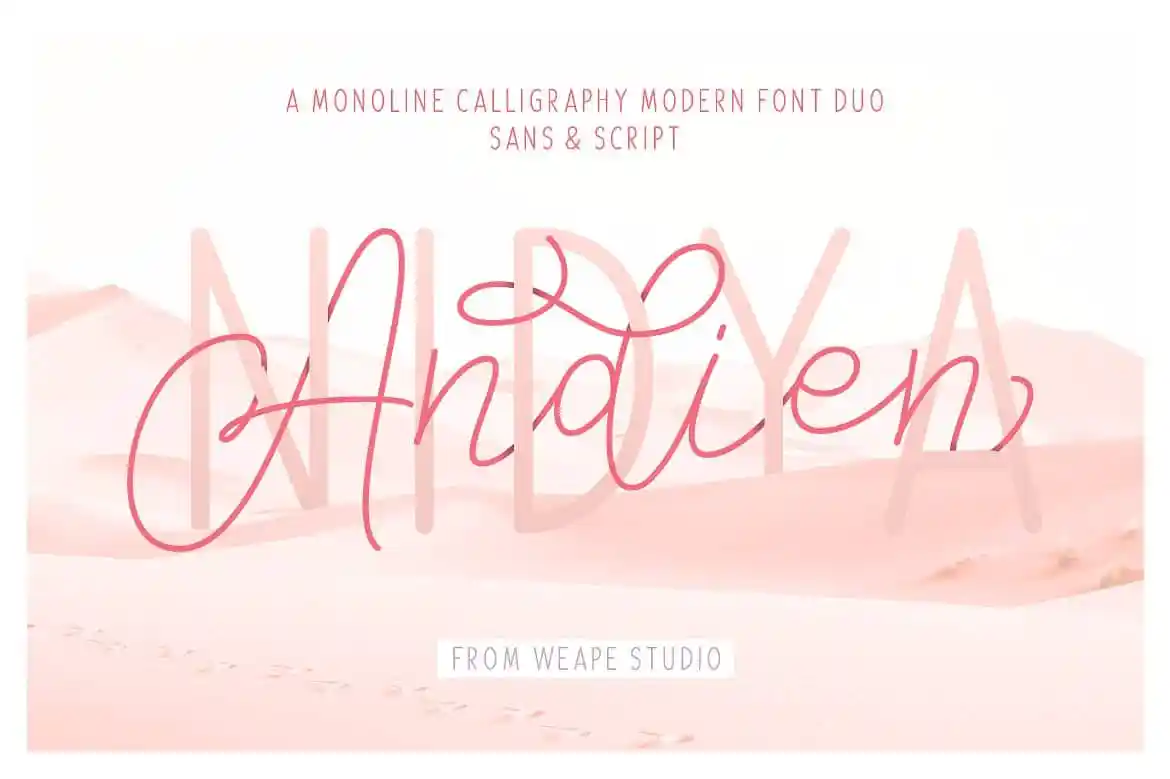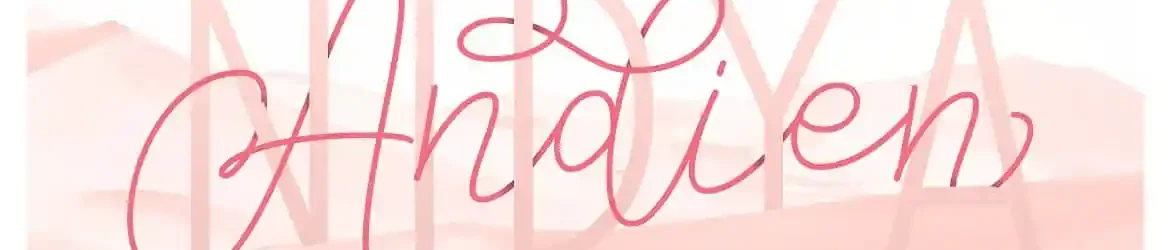
Olá! Estou aqui uma combinação moderna de serif e script, criada pelo 0001themes, no estilo de fontes de registro. Este é um duo de fontes que inclui a sofisticada Andien Nidya Script, uma fonte monoline com traços semicurvos e o sans-serif contemporâneo. A fonte moderna Andien Nidya traz à tona uma modernidade única, combinando características de calligrafia monoline com estilo de script, criando um duo perfeito para designers que buscam um toque único e sofisticado em seus projetos. E você, o usuário, poderá experimentar uma versão de teste de Andien Nidya Font sem comprometer a qualidade do design. Admira essa combinação única de elegância e modernidade com a Andien Nidya Script Font!